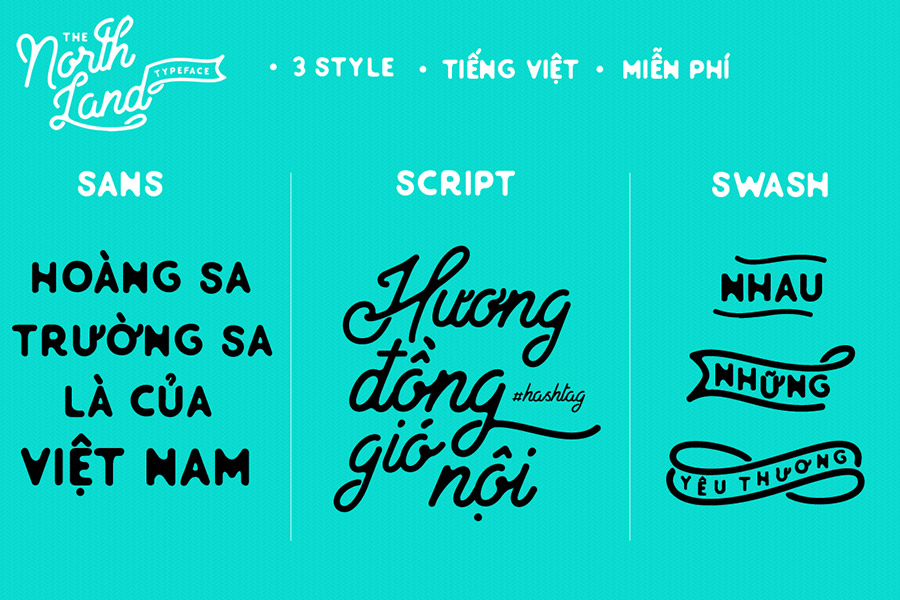
FS North Land là một font chữ cho Photoshop không thể bỏ qua cho những người thích phong cách vintage cổ điển. Màu sắc cổ điển trong font chữ Vintage này vẫn giữ được sự cứng cáp. Nhiều định dạng của FS North Land cho phép phù hợp với nhiều loại dự án. Phong cách này phù hợp với thiết kế website mang phong cách cổ điển.
Font FS North Land thuộc kiểu chữ sans-serif, điều này có nghĩa là nó không có các chân ở cuối các nét chữ, giúp tăng tính hiện đại và sự gọn gàng, dễ nhìn. Với các nét chữ đậm và rõ, font chữ này đặc biệt phù hợp cho các thiết kế banner, poster, logo, và thậm chí là trong các dự án branding.
FS North Land là font chữ mang đến sự chuyên nghiệp và ấn tượng cho bất kỳ dự án thiết kế nào trên Photoshop. Với thiết kế mạnh mẽ, dễ đọc và khả năng linh hoạt, FS North Land không chỉ giúp tác phẩm của bạn nổi bật mà còn truyền tải phong cách cá nhân và thương hiệu của bạn. Hy vọng với bài viết này của Hubservices, bạn đã có cái nhìn chi tiết về FS North Land và cách sử dụng nó để tạo nên những sản phẩm thiết kế đẳng cấp.